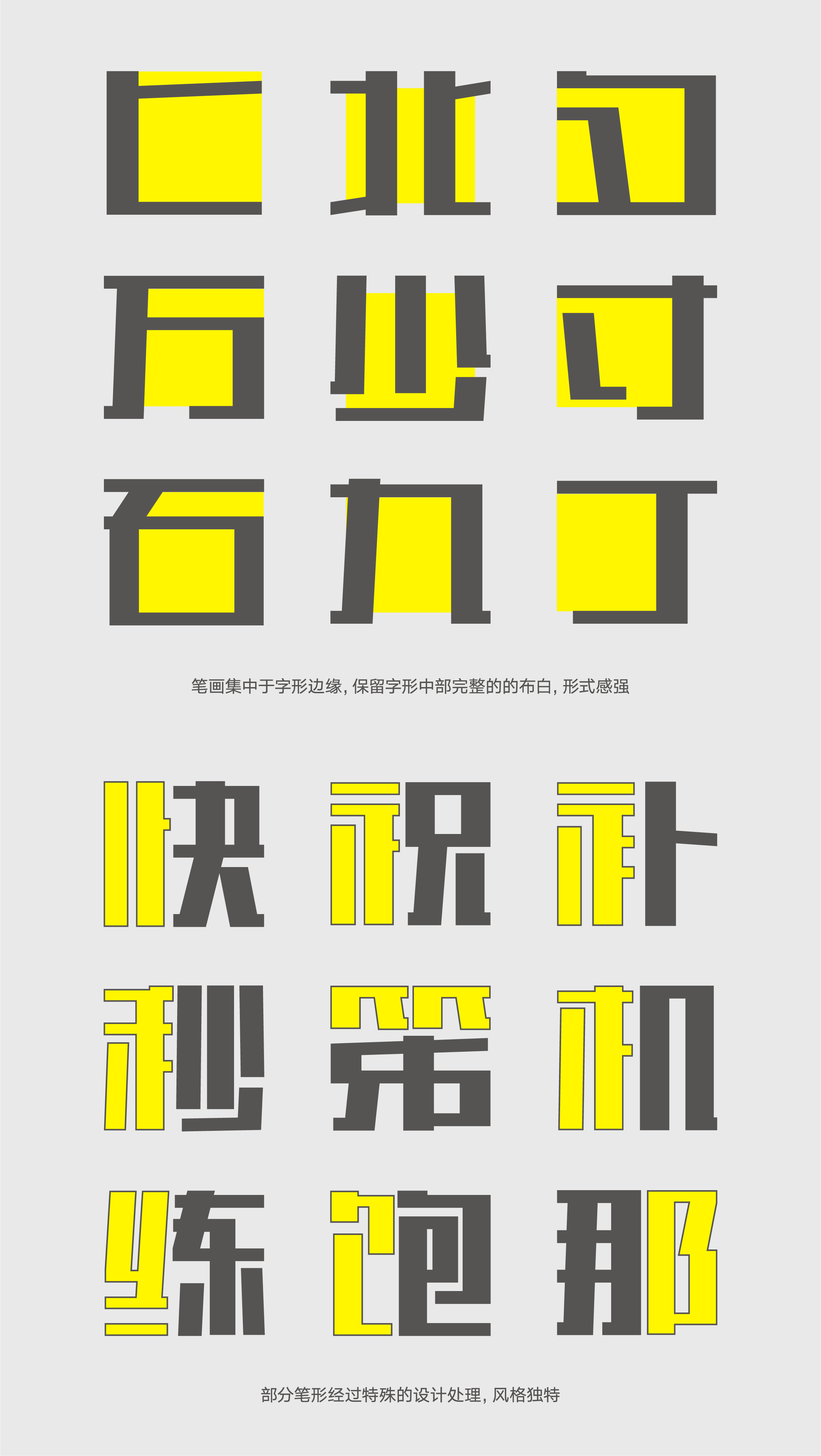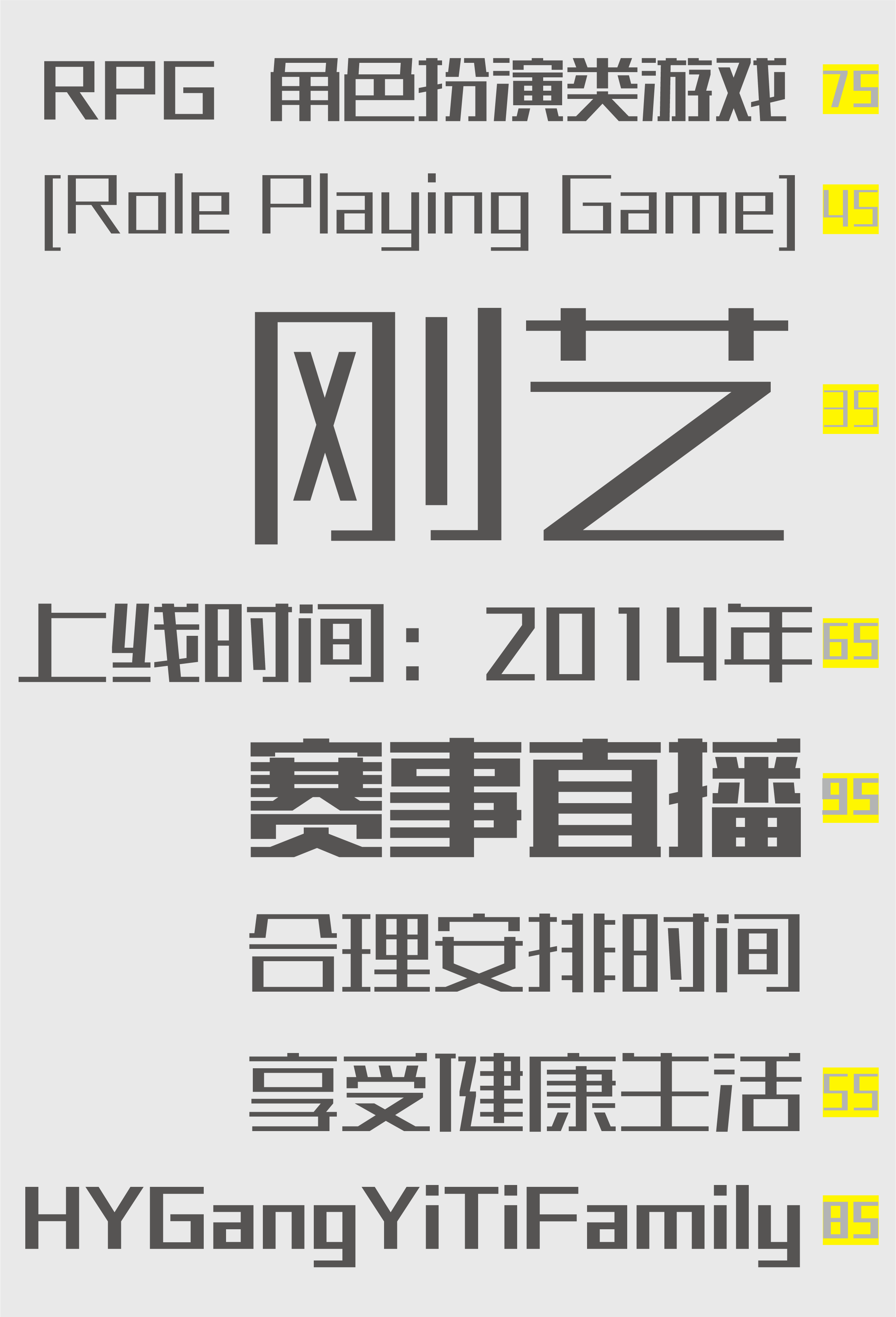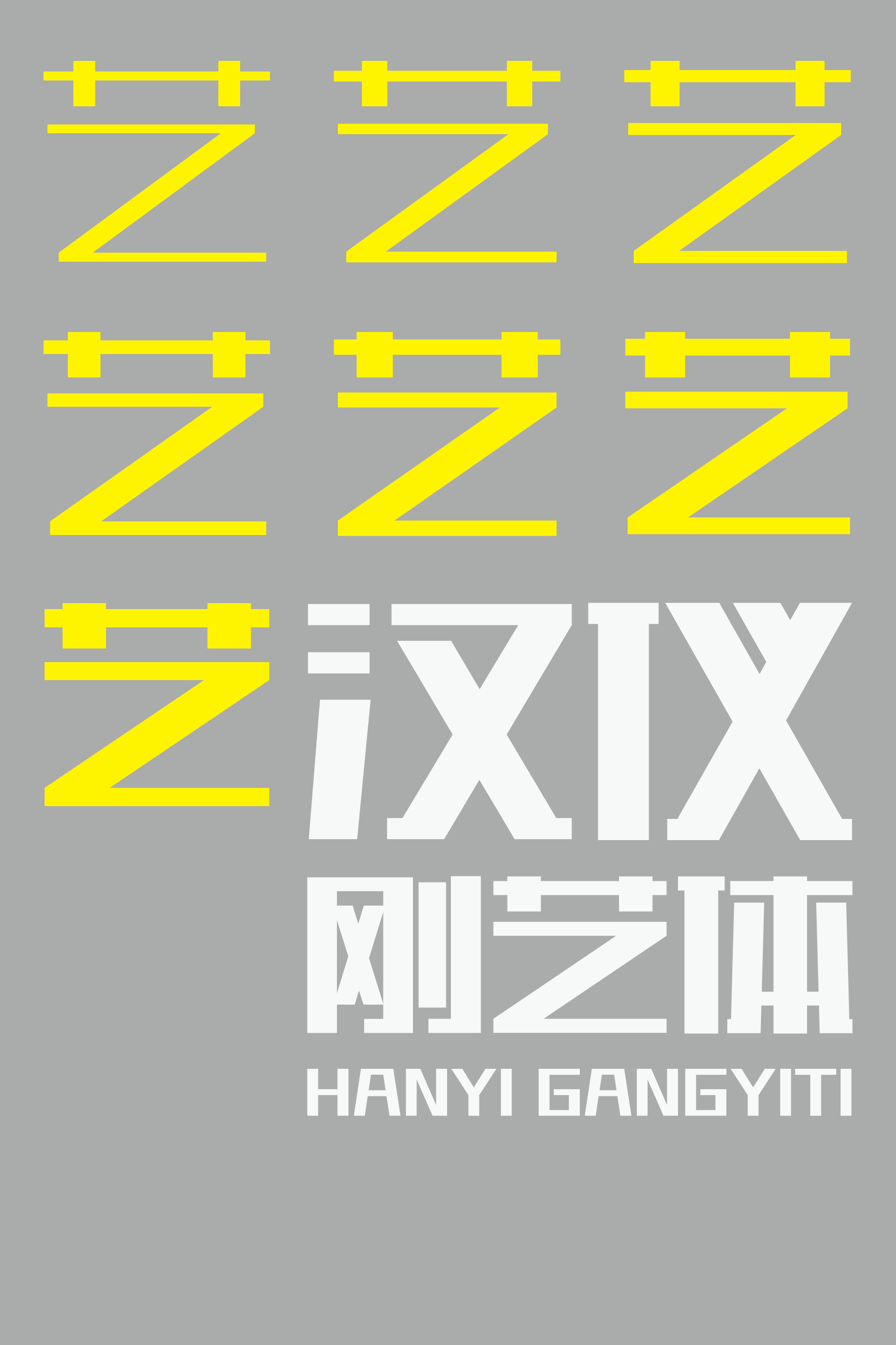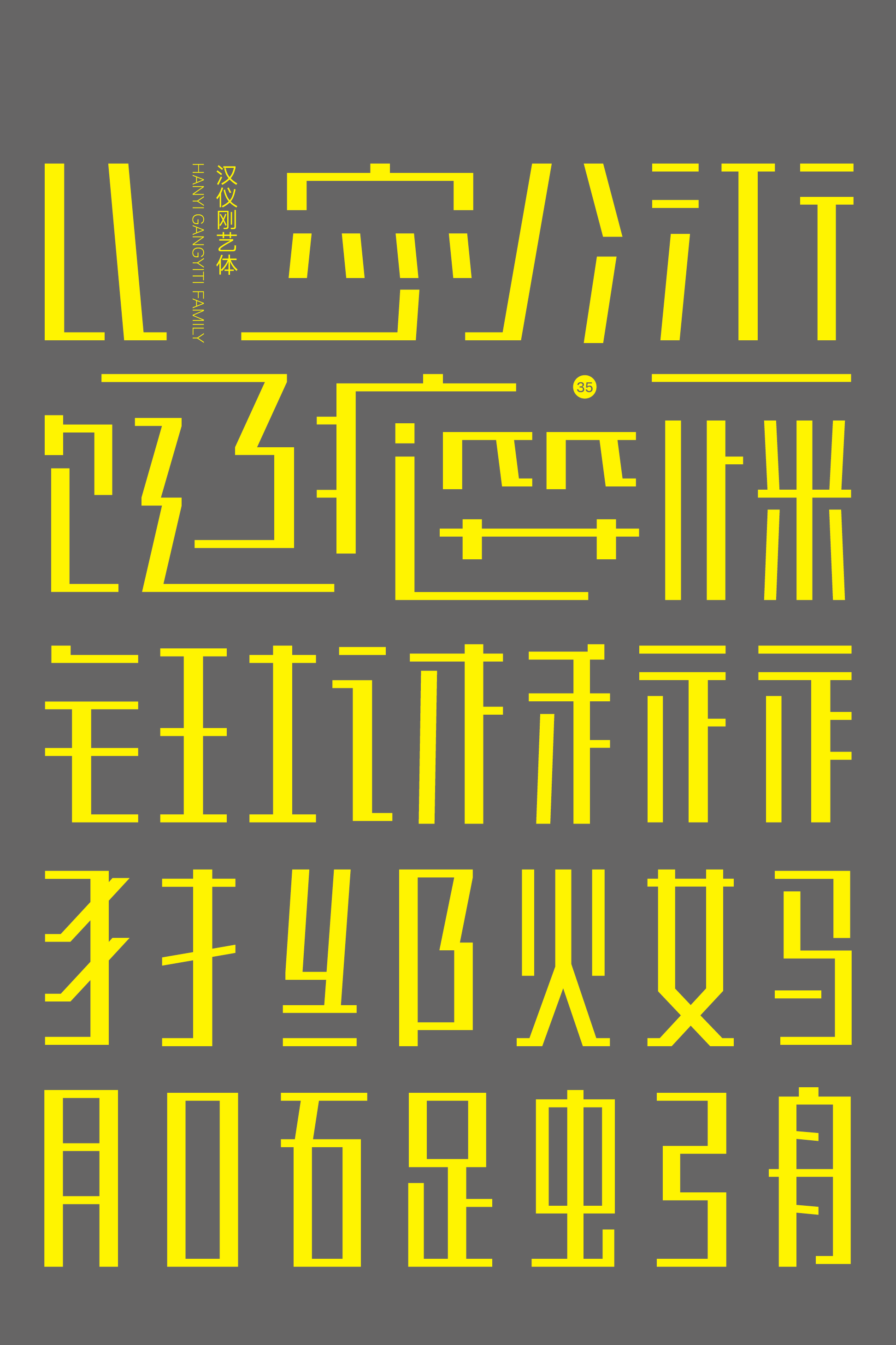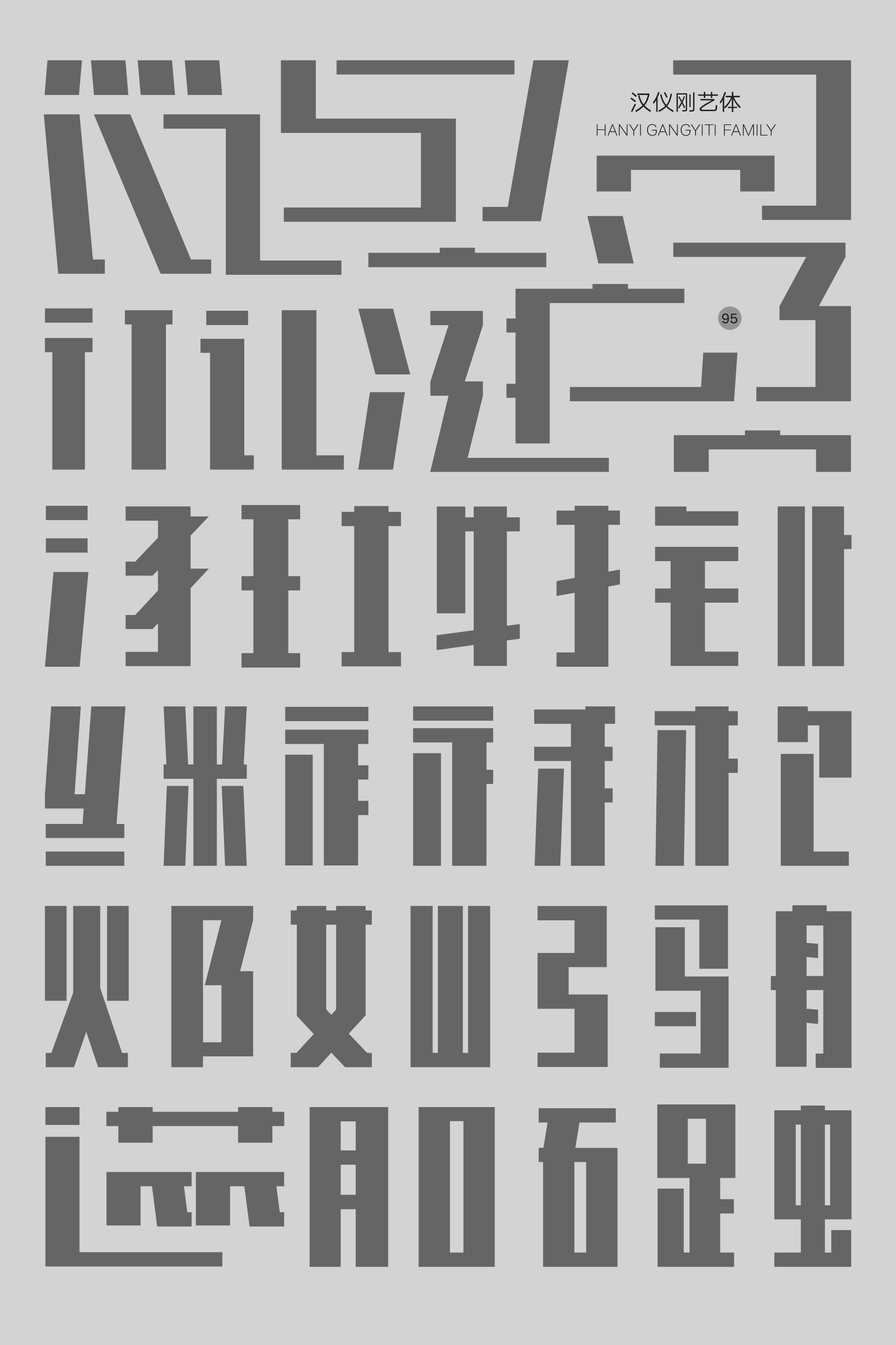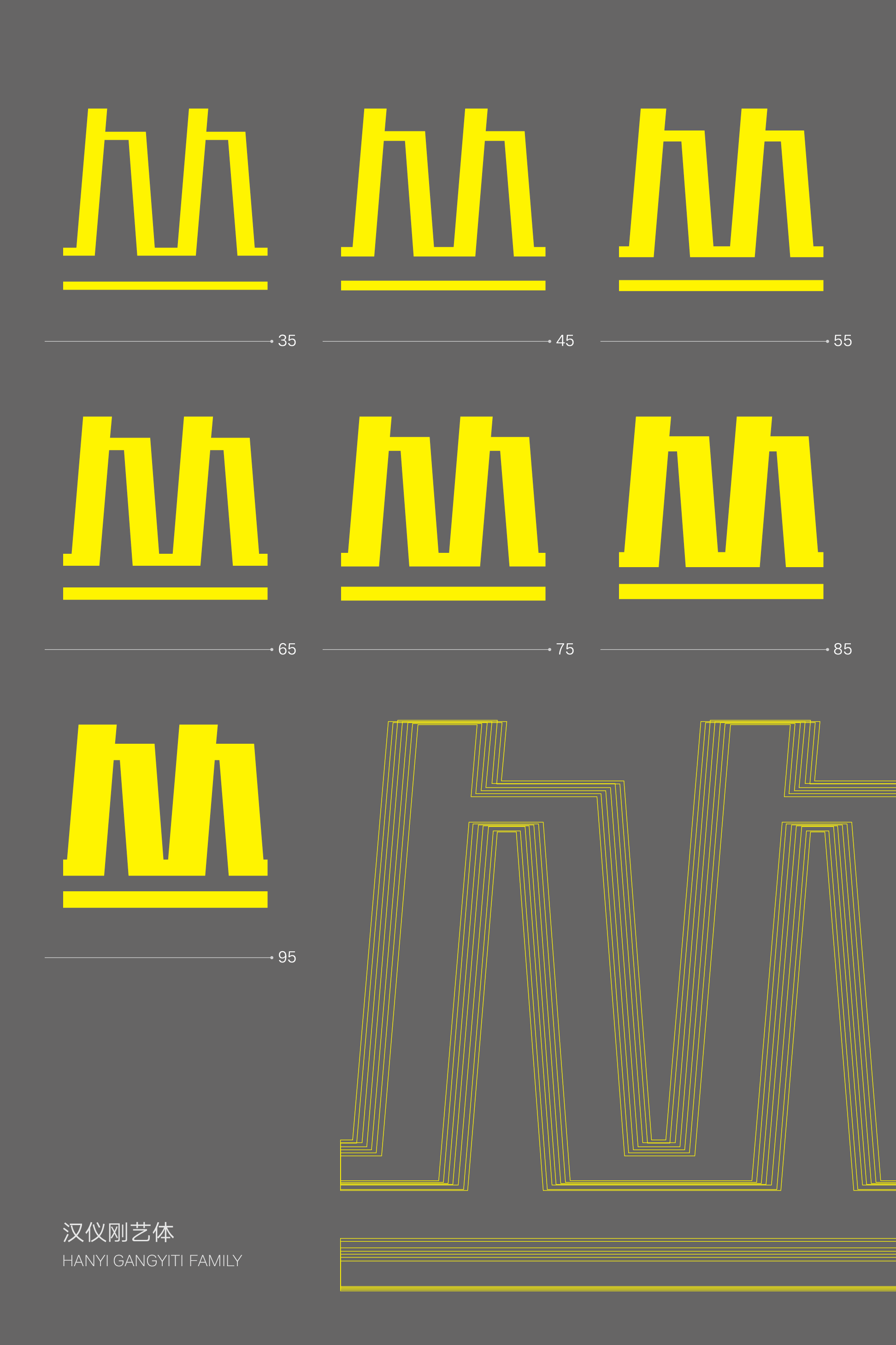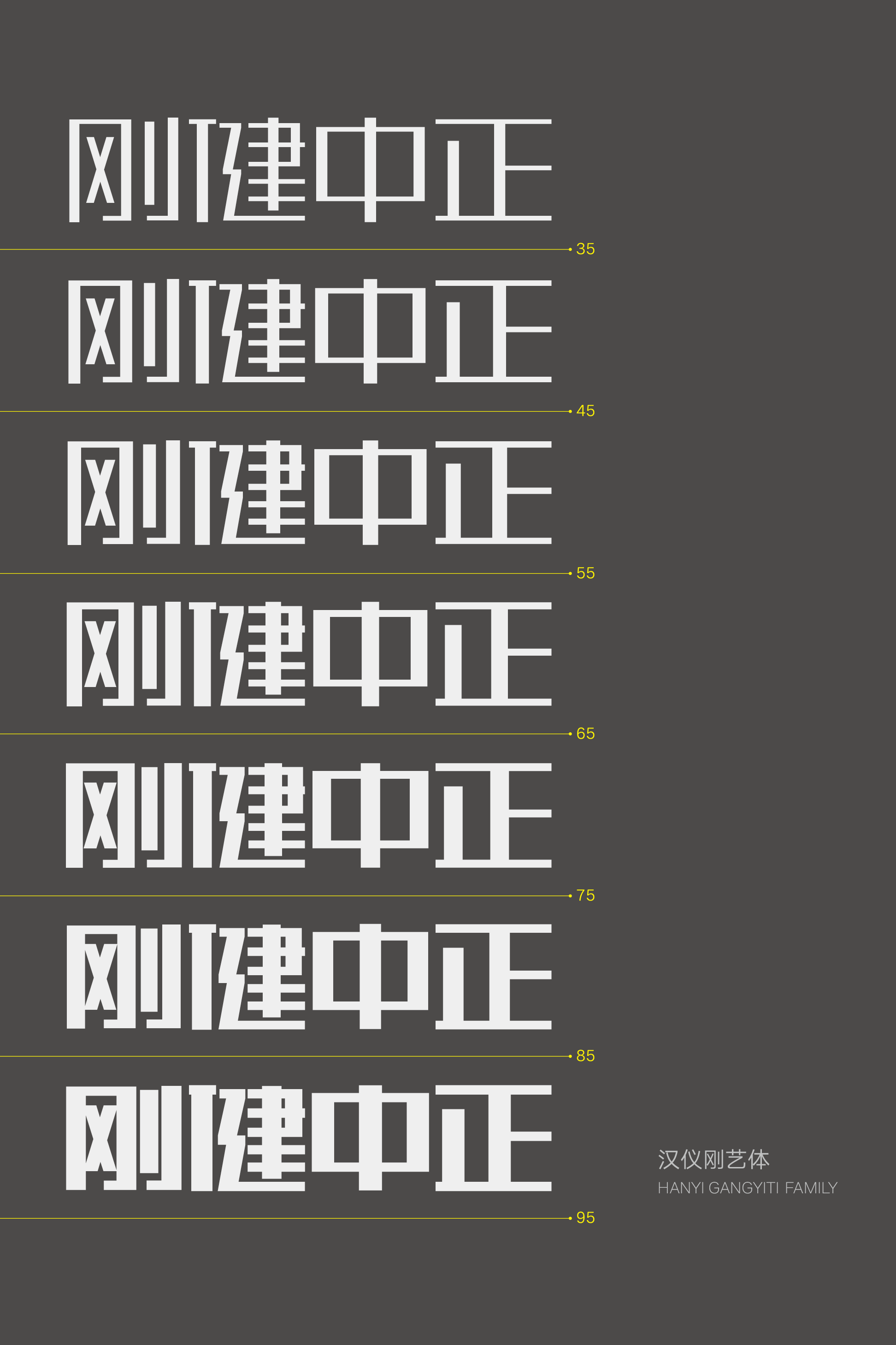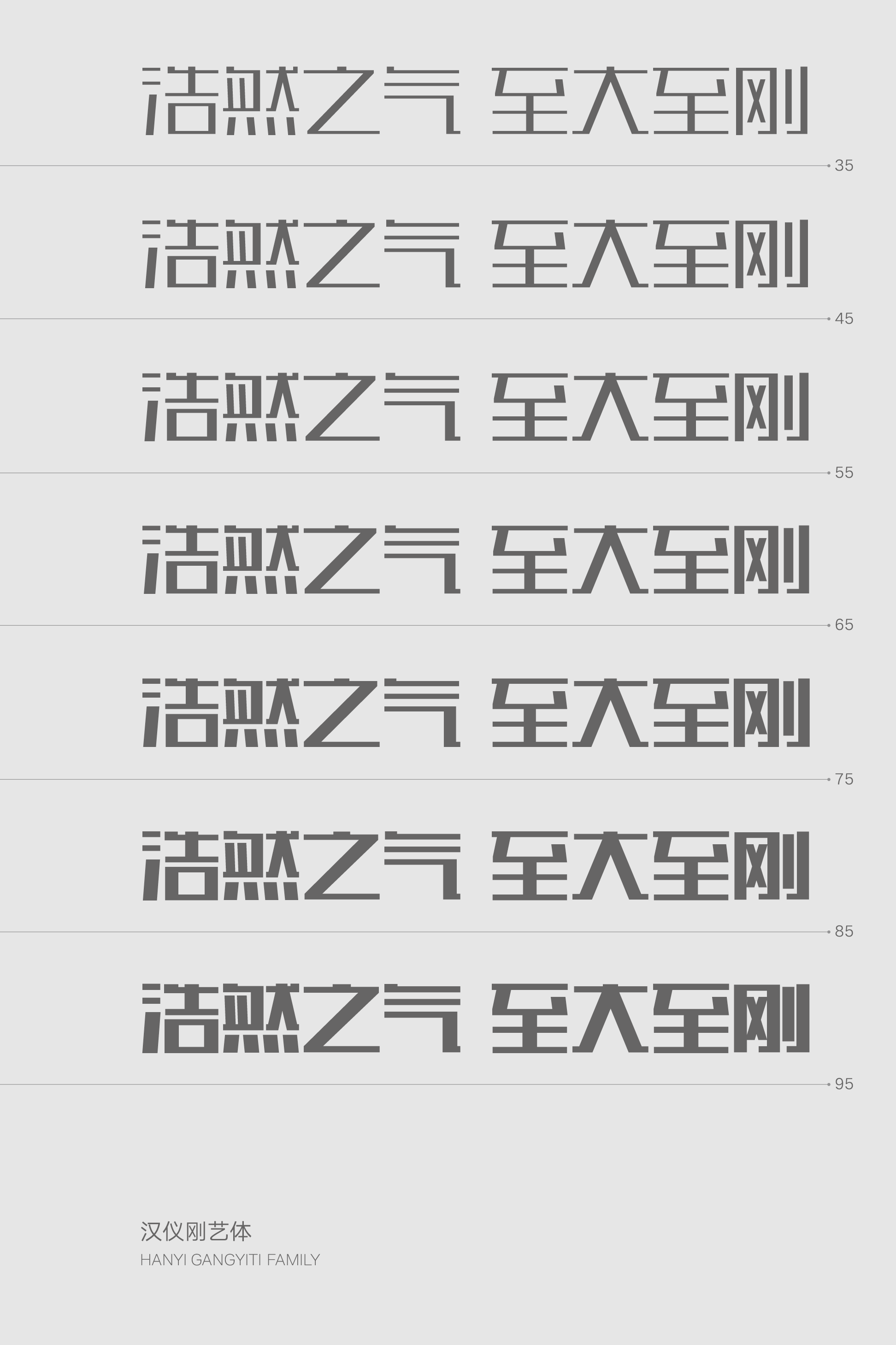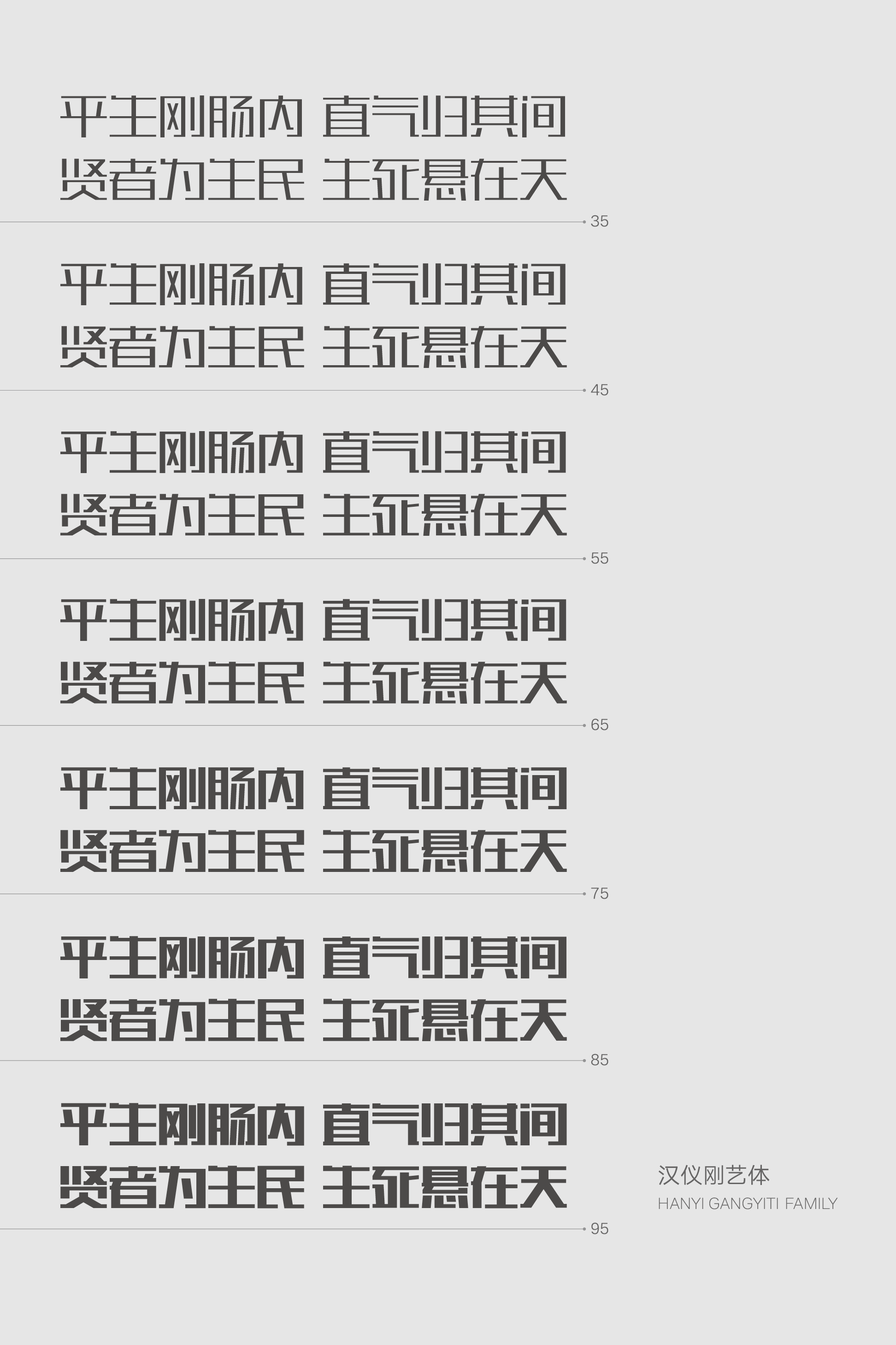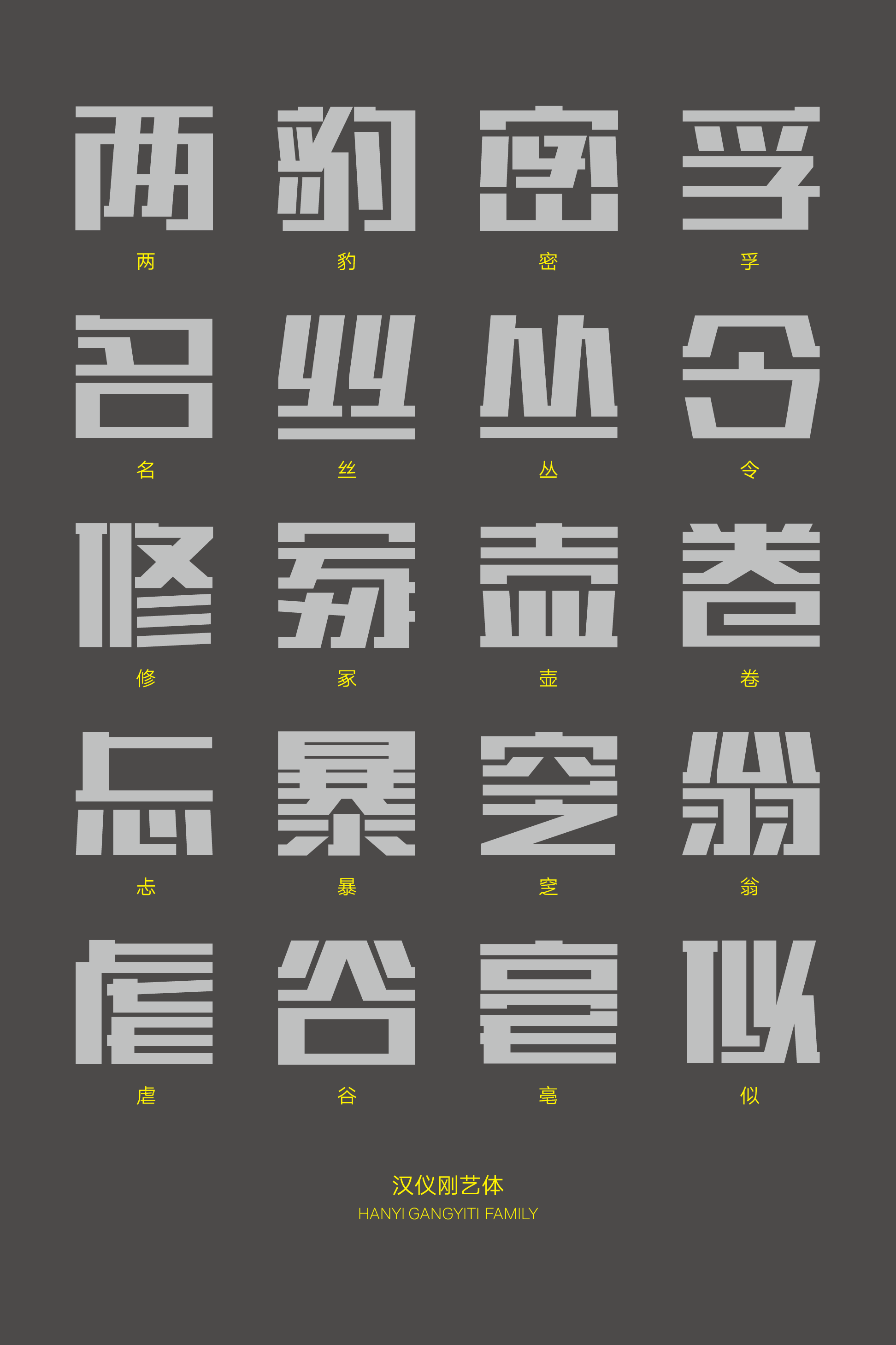
汉仪刚艺体
汉仪刚艺体,以金属般刚硬的全直线构成,字形扁宽,敦实有力。横笔细劲,表现出金属的质感;撇捺出脚,表现出金属的硬度。这款字体风格强烈,刚毅而具有艺术风格,拓展成为由粗到细共7种字重的家族字体,满足正文标题的全方面排版需求,适用于体育赛事、运动竞技、休闲娱乐等使用场景。
字形扁宽,敦实有力。
笔画由金属般刚硬的全直线构成。
撇捺出脚具有金属的硬度,同时平衡了字形。
横笔细而刚劲,表现出金属的质感。
笔画集中于字形边缘,特殊笔形处理和排布方式强化了这款字体的风格性。
西文部分同样以全直线构成,刚劲有力,具有金属质感。
汉仪刚艺体家族包含由粗到细共7种字重,满足正文标题的全方面排版需求,适用于体育赛事、运动竞技、休闲娱乐等使用场景。